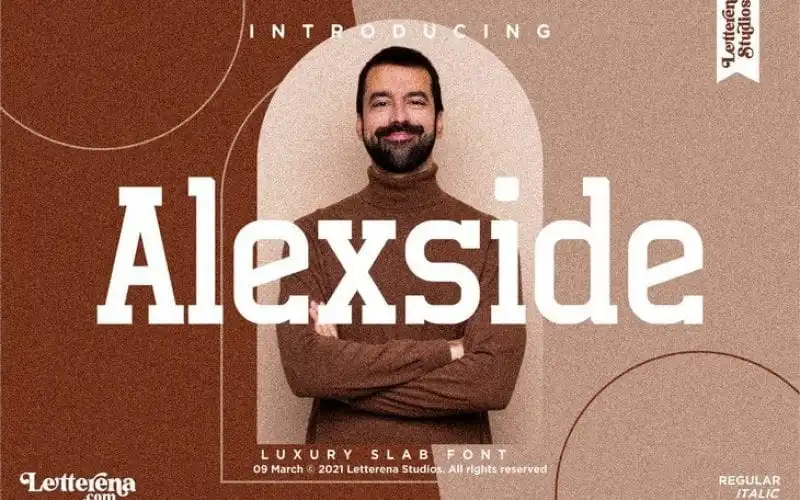
Alexside Slab Serif Font – Download Grátis
A ‘Alexside Slab Serif Font’ é uma tipografia slab serif condensada produzida pela Letterena Studios. Este tipo de letra foi cuidadosamente criado a mão, mantendo um estilo moderno e vintage perfeito para projetos variados como logotipos, designs de marca, embalagens de produtos, pacotes de chá, etiquetas de alimentos, revistas e livros. Suas linhas robustas e suas proporções compactas fazem dela uma escolha ideal para um amplo espectro de aplicativos, desde designs de móveis até convites de casamento ou cartões postais. A sua elegância perfeita se adequa a todos os seus projetos luxuosos e belos que requerem um sabor premium de slab serifa.